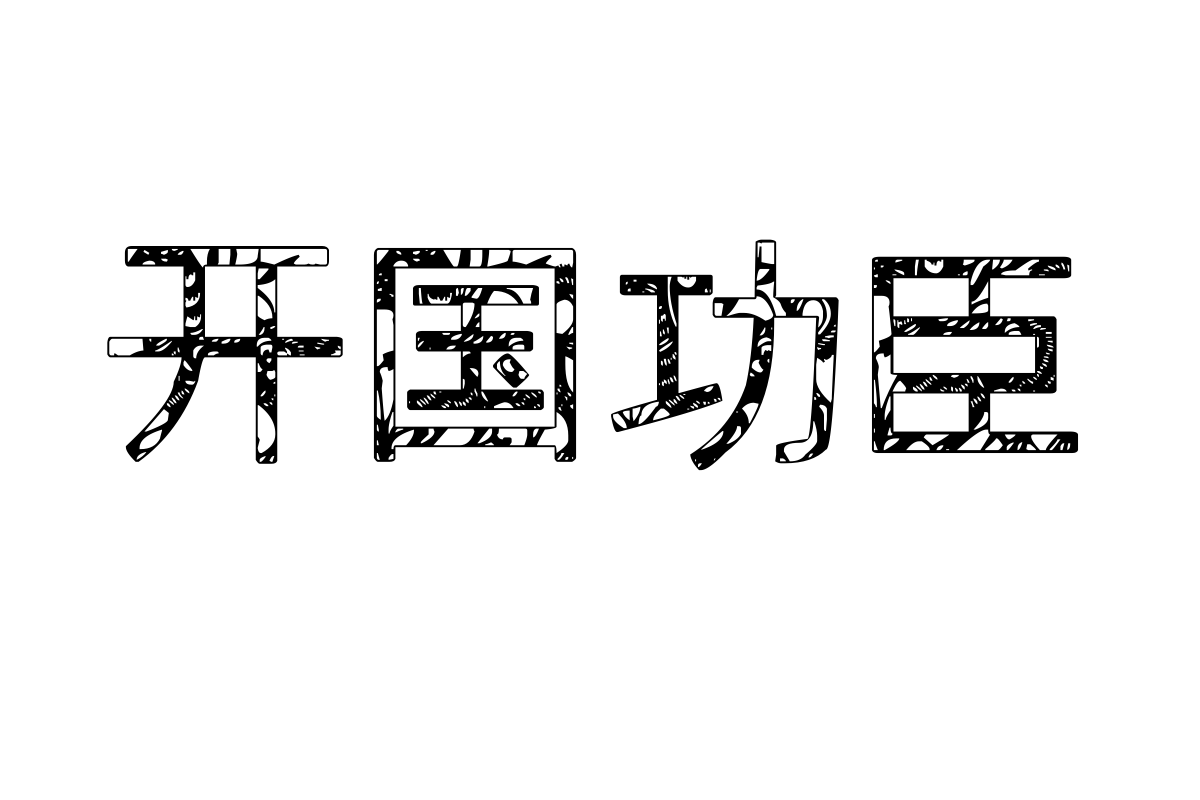
斑马窗花中的黑体字体是一种具有独特视觉效果的中文字体。这种字体的特点是其笔画粗细不一,呈现出一种类似于斑马身上的黑白条纹图案。这种设计使得字体看起来更加生动有趣,同时也增加了阅读时的趣味性和视觉冲击力。
斑马窗花中的黑体字体适用于各种需要突出视觉冲击力和趣味性的场合,如广告、宣传册、海报等。它的使用可以有效地吸引观众的注意力,提高信息的传达效果。